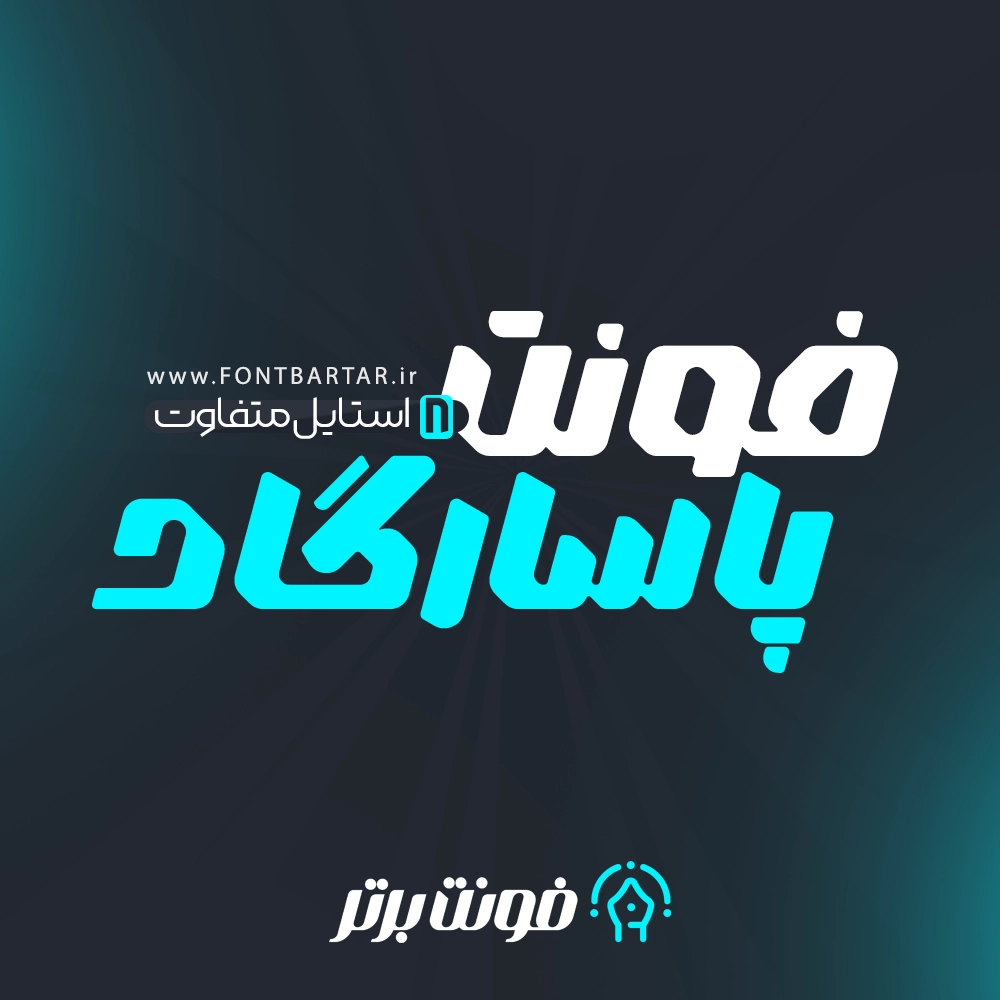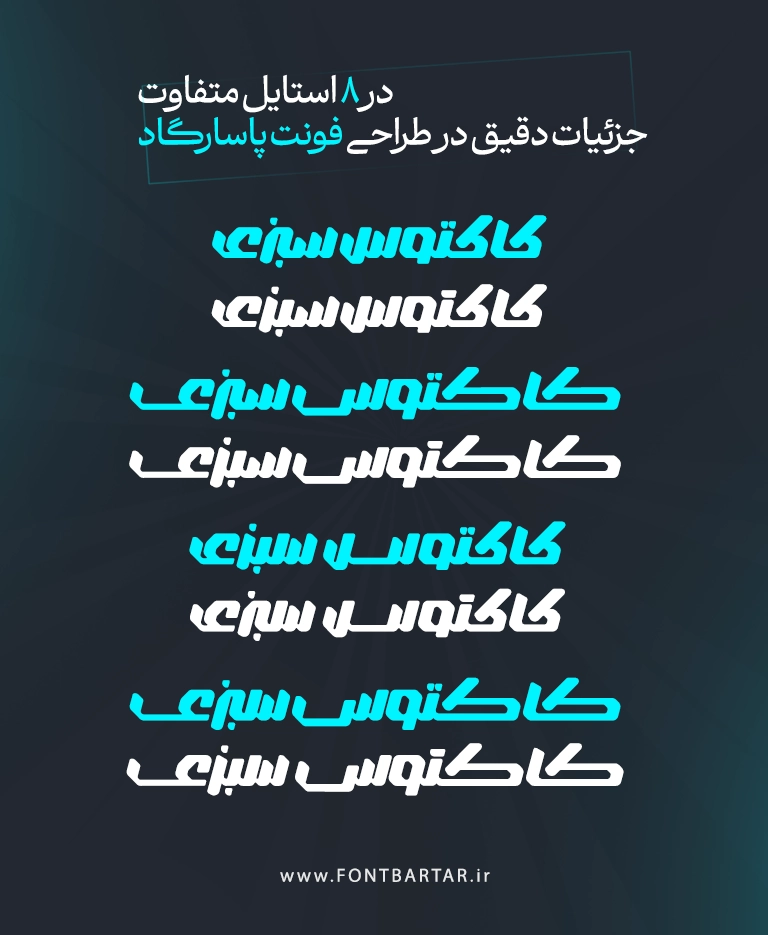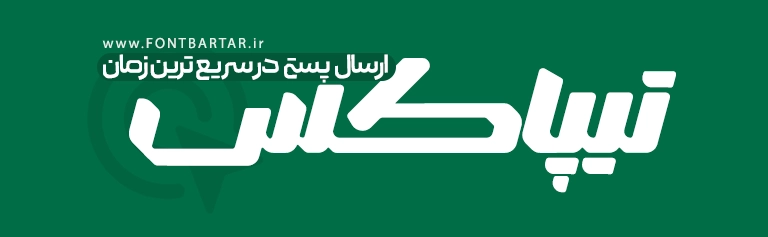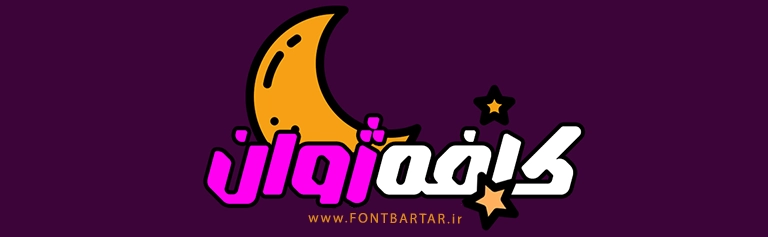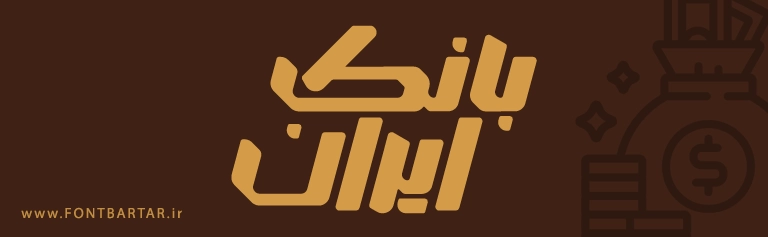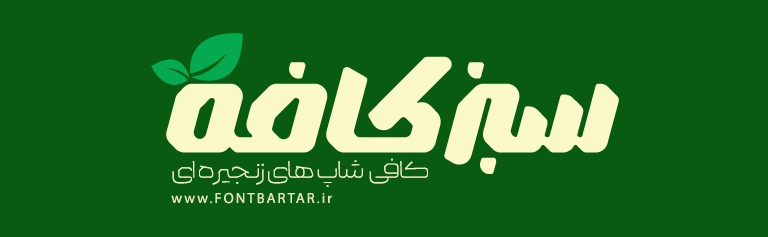
فونت پاسارگاد
Pasargad Font
دانلود فونت پاسارگاد | فونت مدرن فارسی با ۸ استایل متفاوت
اگر به دنبال یک فونت فارسی حرفه‌ای و منعطف برای طراحی‌های گرافیکی، صفحات وب یا تولید محتوای دیجیتال هستید، فونت جدید پاسارگاد انتخابی بی‌نظیر برای شماست. این فونت خاص با ۸ استایل متنوع و مدرن طراحی شده تا نیازهای مختلف طراحان را در پروژه‌های متفاوت پوشش دهد.
ویژگی‌های منحصربه‌ فرد فونت جدید فارسی پاسارگاد :
• مناسب برای طراحی لوگو، بنر تبلیغاتی، تایپوگرافی و تولید محتوا
فونت جدید برای ادیت در 8 استایل
استایل های فونت پاسارگاد
چرا فونت فارسی خاص پاسارگاد را انتخاب کنیم؟
با گسترش فضای دیجیتال و افزایش اهمیت طراحی بصری، استفاده از یک فونت حرفه‌ای فارسی نقش مهمی در جذابیت و کارایی پروژه‌های شما دارد. فونت زیبا پاسارگاد با طراحی چشم‌نواز و استایل‌های متنوع، مناسب طراحان گرافیک، توسعه‌دهندگان وب و تولیدکنندگان محتوا است که به کیفیت و تمایز اهمیت می‌دهند.
فونت لوگوتایپ پاسارگاد
Farsi Font Pasargad
Pasargad font
فونت جدید پاسارگاد
کاربردهای فونت پاسارگاد :
🖋️ طراحی لوگو تایپ فارسی
🎯 طراحی رابط کاربری (UI/UX)
📢 پوستر و بنرهای تبلیغاتی
📱 اپلیکیشن‌های موبایل و وب‌سایت‌ها
✍️ تولید محتوا و طراحی تایپوگرافی فارسی
📚 استفاده در چاپ و انتشارات